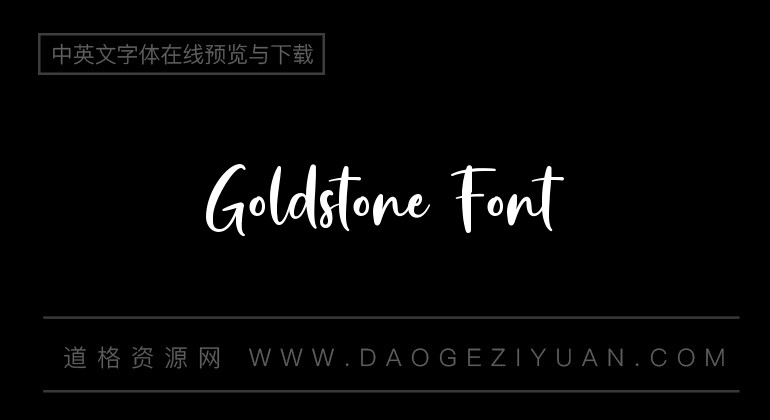
Goldstone Font
Goldstone Font 是一款免费的中英文手写风格字体,它由设计师 Jack Wassiliauskas 创作。该字体的特点是类似于手写的感觉,字母有着不规则的线条,让文本看起来更加自然和有机。此外,Goldstone Font 还具有良好的可读性和清晰度,使其可以用于各种设计项目中,如海报、名片、标志、书籍等。该字体有三种字重可用,包括 Light、Regular 和 Bold,可根据需要选择合适的字重。Goldstone Font 的设计简单而现代,适合需要独特风格的设计师和艺术家使用。
Goldstone Font是一款非常不错的手写艺术字体,具有很好的视觉感,适合于文化类的宣传设计、商业类品牌的广告和产品包装设计以及个性化文字排版等较多场景。